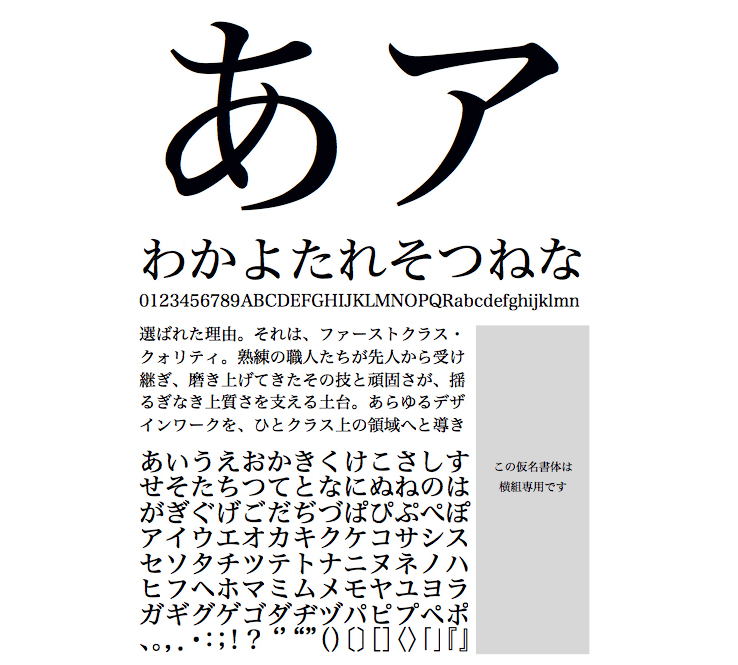
仮名・英数字グリフのみ収容
※本商品は仮名書体です。ギャラリーの見本に含まれる漢字はヒラギノ明朝を使用しています。
【ヒラギノ明朝横仮名】「ヒラギノ明朝」のデザインに合わせた横組み用の仮名書体です。横組ベタ送りの組版でも字間に粗密が少なく、美しくラインが揃うように、組まれた版面の濃淡が均一になるようにデザインしています。